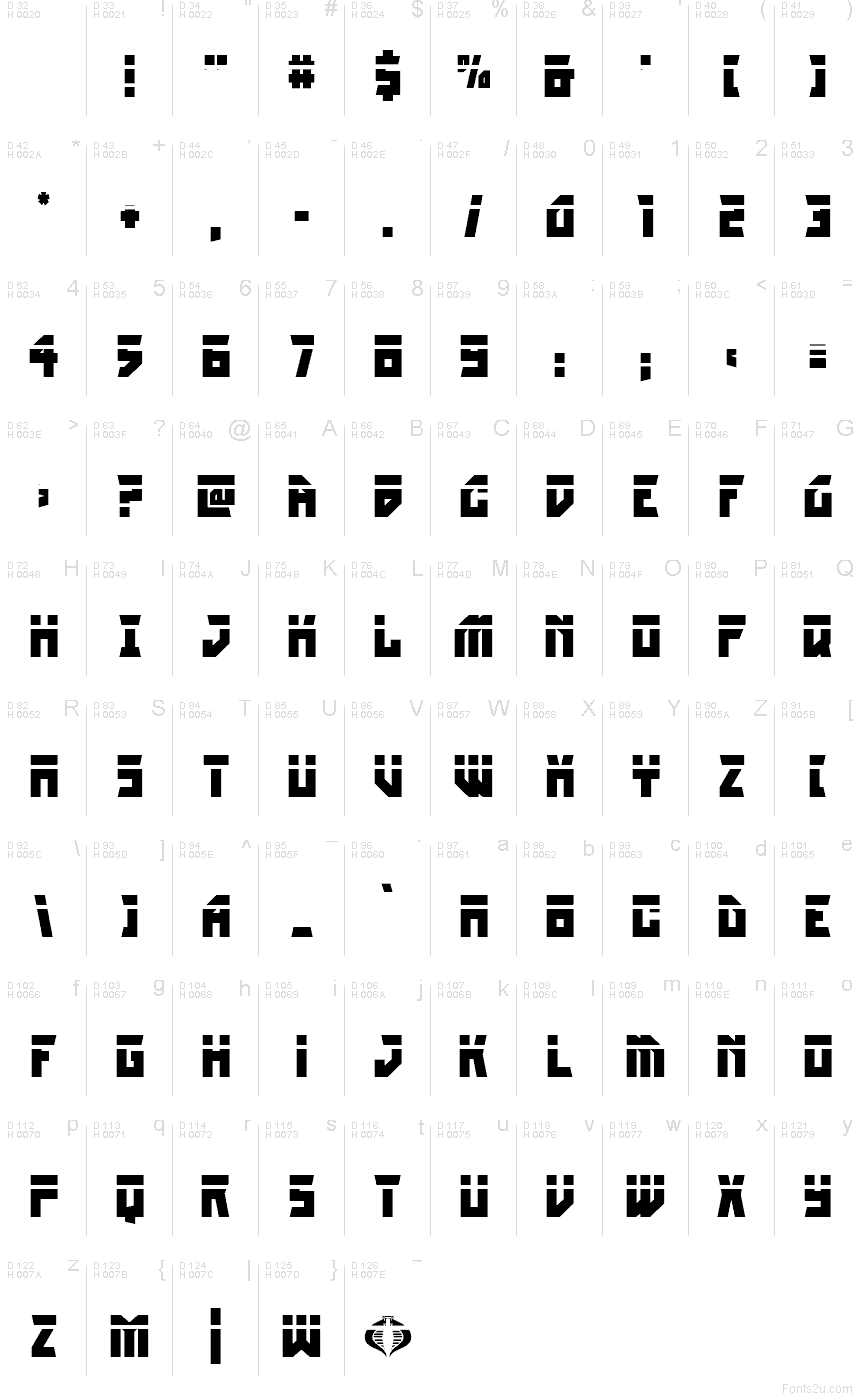
Omni-cobra Straight Laser
Omni-Cobra Straight Laser de Iconian Fonts es una tipografía display gratuita de estilo futurista, definida por cortes rectos y precisos y estrechas aberturas geométricas en cada letra. Sus formas segmentadas y angulares, con bordes verticales duros y diagonales puntiagudas, le confieren un carácter de estilo stencil cortado con láser, ideal para la ciencia ficción.
Omni-Cobra Straight Laser funciona de maravilla en títulos de juegos, pósteres de ciencia ficción, branding tecnológico, arte de álbumes y detalles de logotipos, ya que sus formas recortadas transmiten una marcada estética mecánica y codificada. Esta tipografía gratuita también es perfecta para gráficos de eventos digitales, encabezados de pósteres y etiquetas de interfaz cuando buscas un estilo de letra que se sienta más diseñado y técnico que manuscrito.